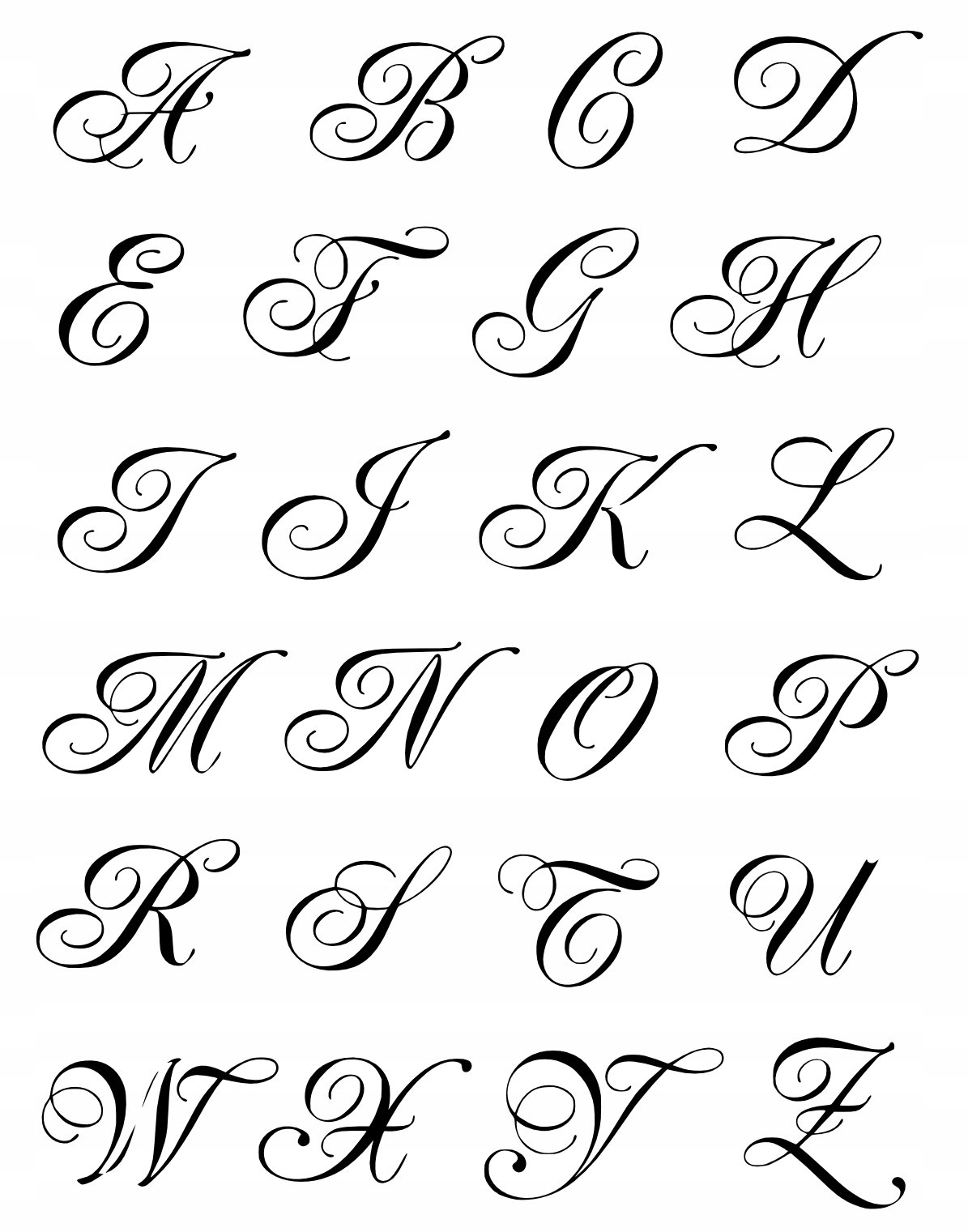
Основы леттеринга. С чего начать?
В этом уроке мы изучим строение букв, узнаем об основах леттеринга, научимся рисовать буквы из наборных шрифтов.
Перед изучением букв нам надо познакомиться с основными шрифтами и понятиями в типографике.
В леттеринге используются три основных типа шрифта: антиква, гротеск и рукописный.
Основные классы шрифтов для леттеринга
Антиква
Антиква — класс шрифтов с засечками, произошедших от римского монументального письма.
Это контрастные шрифты, в которых, как правило, вертикальный штрих намного толще горизонтального.
Контрастность — характеристика шрифта, обозначающая соотношение толщины основного и дополнительного штриха. Если разница большая, то шрифт контрастный, если маленькая, то неконтрастный.
В леттеринге используются только прописные буквы алфавита. Острые нижние засечки, «надетые» на знак, напоминают обувь, делают шрифты более устойчивыми. Если вам нужно сбалансировать композицию, смело используйте антикву.
Гротеск
Гротеск — тип шрифтов без засечек.
Горизонтальные и вертикальные штрихи имеют одинаковую толщину, что делает шрифт простым в исполнении. Такой шрифт хорошо сочетается с каллиграфическими шрифтами с большим количеством росчерков. Гротеск подходит для написания длинных слов, а также для заполнения сложных форм: ленточек, рамочек.
Рукописный шрифт
Рукописный шрифт (или скрипт) — имитация каллиграфических стилей.
Иллюстрация из книги «Буква к букве»Вы можете чередовать буквы рукописного стиля и антиквы в одном слове, потому что в своей основе они имеют контрастный штрих и хорошо сочетаются.
Неконтрастными чаще бывают гротески, а контрастными — антиквы, хотя есть и экзотические примеры, когда все наоборот.
ГЛАВНОЕ, ЧТО НАДО ПОНЯТЬ: ШРИФТ — ЭТО СИСТЕМА, БУКВЫ В НЕЙ ЕДИНООБРАЗНЫ.
Основные понятия в типографике
Вы когда-нибудь слышали слова «кёрнинг», «трекинг», «интерлиньяж»? Вам что-то говорят термины «наплыв», «капля», «хвост»? Давайте разбираться, что это такое.
Кёрнинг — это расстояние между буквами. Чтобы в словах не было «дыр», это расстояние нужно правильно распределить.
Трекинг — это совокупность межбуквенных просветов во фразе или предложении.
Интерлиньяж — расстояние между строками.
Изображение ниже наглядно показывает из чего состоят буквы.
Иллюстрация из книги «Буква к букве»Жирные вертикальные и диагональные штрихи называются основными, во всех знаках одного шрифта они должны выглядеть одинаковыми. Наплывы овалов и полуовалов должны быть зрительно такой же толщины, как основные штрихи.
Дополнительные штрихи называются соединительными, они более тонкие, если шрифт контрастный.
Буквы, как птицы на ветке, сидят на базовой линии. Части, выходящие за нее, называются верхними и нижними выносными элементами. Дырки от полуовалов и овалов — внутрибуквенный просвет.
Красивый пластичный элемент — капля — встречается не во всех шрифтах, она очень украшает буквы. В антикве есть особенные элементы — засечки, они бывают односторонними и двусторонними. Апроши, межбуквенные интервалы, — расстояния между соседними буквами — также должны быть зрительно уравновешены. Специалисты выделяют и другие элементы, но для наших задач этих понятий будет достаточно.
Межбуквенные расстояния
Из-за того, что все буквы разной формы, нельзя делать расстояния между ними одинаковыми.
Самое большое расстояние нужно делать между соседними вертикальными штрихами. Немного меньшее расстояние будет, если вертикальный штрих одной буквы граничит c округлым штрихом
другой буквы. Еще меньшее расстояние будет между двумя округлыми элементами. И еще меньшее, если прямые и округлые штрихи встречаются с диагональными соседями (А, У, Ж, а также Г, Т, если мысленно соединить их крайние точки).
Проще говоря, площади промежутков между разными буквами за вычетом внутрибуквенного пространства должны сближаться.
В этом примере расстояния между буквами механически одинаковые и не учитывают разность форм. В итоге мы получаем неравномерную надпись.
Часто на карандашном контурном рисунке непонятно, что надпись получилась неравномерной, и только когда вы уже все зальете черным, это становится видно. Через некоторое количество работ ваши глаз и рука натренируются, и будет получаться делать равномерно сразу.
Практическое задание
Когда мы разобрались с межбуквенным расстоянием и познакомились с основными шрифтами, пришло время потренироваться. Сначала попробуйте написать несколько слов на прямой строке, а затем на наклонной, волнистой, на уменьшение и на увеличение.
Обратите внимание, что при написании букв по наклонной на увеличение или уменьшение, все вертикальные линии остаются вертикальными, а угол меняется только у горизонтальных элементов.
Затем можно попытаться вписать слово в простую фигуру, овал или многогранник.
Теперь пришло время придать скелету нашего алфавита какую-нибудь форму. Для этого можно использовать антикву, гротеск или брусковый шрифт (как гротеск, только с засечками).
Теперь переходим непосредственно к шрифтам.